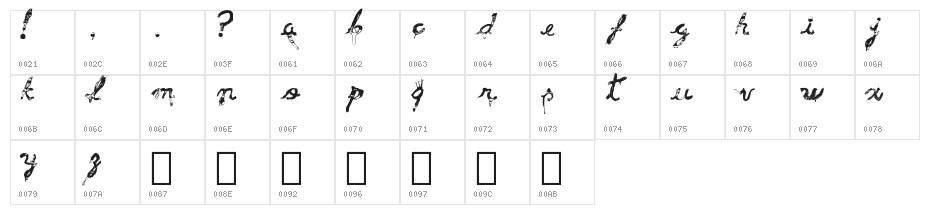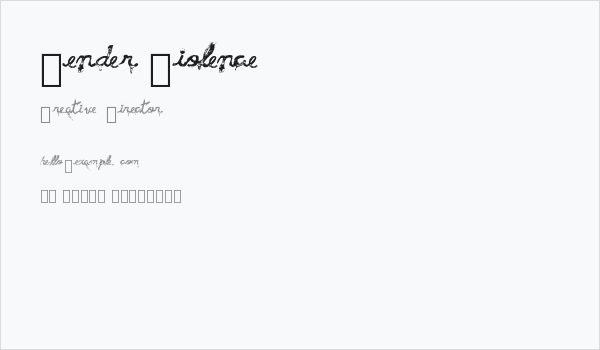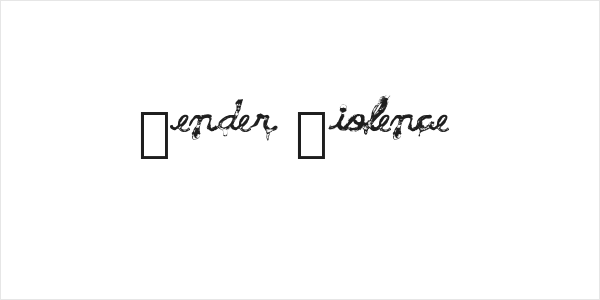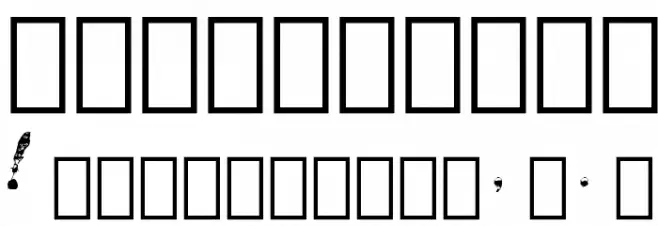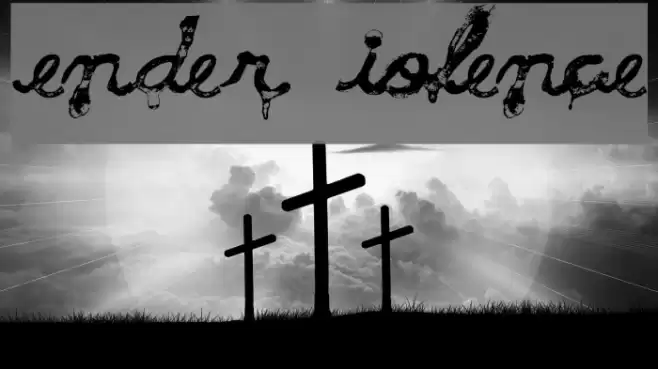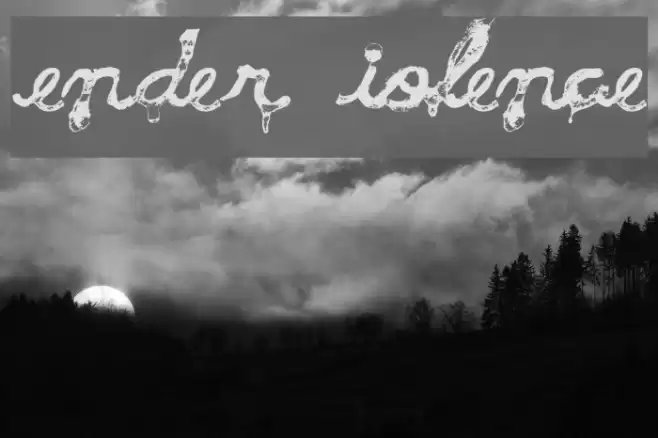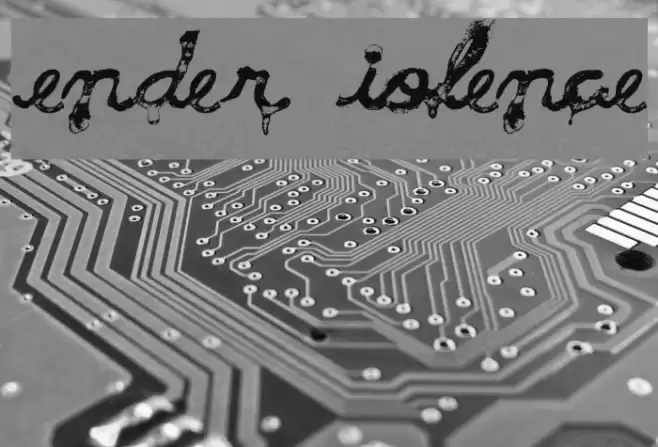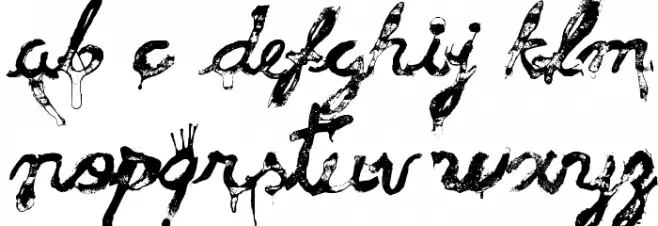
Gender Violence Font
✎ Script
Esta fuente incluye 43 caracteres. Haz clic en cualquier carácter para ver los detalles.
| Caso de uso | Logos, Headlines, Artistic projects |
| Proyectos propuestos | Ideal for album covers, protest posters, edgy branding, or artistic projects that require a bold statement. |